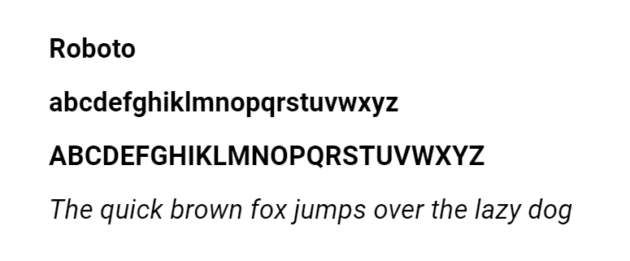
Les meilleures polices de sites Web et comment choisir la bonne
Publié: 2022-02-11De la palette de couleurs aux polices et à la conception du titre, chaque petit détail compte si nous parlons d'un grand projet numérique comme votre site Web. L'utilisation de différentes polices et effets de police peut avoir un impact à la fois négatif et positif sur vos utilisateurs, et c'est à vous de décider si cela sera positif ou négatif. L'équilibre, une manière harmonieuse de relier tous ces détails en une seule création bien organisée, est d'une importance primordiale pour chaque designer numérique.
Les polices et les effets de police sont le meilleur moyen d'atteindre cet équilibre car, pour la plupart des pages Web, la quantité la plus importante de données visuelles est occupée par le corps du texte, les titres et les en-têtes. Par conséquent, vous pouvez ajuster le nombre de détails simples et complexes afin d'obtenir le résultat parfait.
Ouvrir Sans
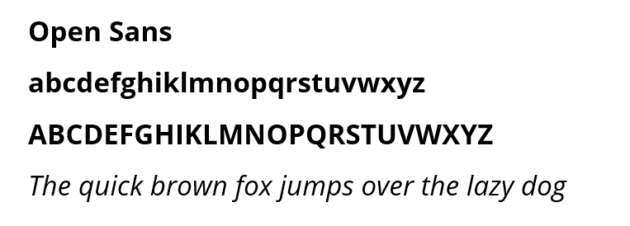
Open Sans fait partie des polices de caractères sans empattement destinées à offrir la meilleure lisibilité et expérience utilisateur. Cette police Web est le meilleur choix pour les sites Web minimalistes avec beaucoup d'informations à consommer (blogs, articles informatifs, etc.). Un autre grand avantage de cette police est sa compatibilité avec de nombreux styles différents.
Lato
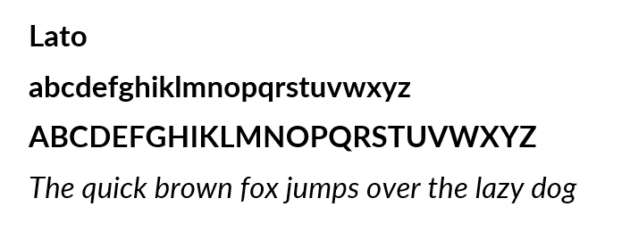
Lato est l'une des meilleures polices à utiliser si votre site Web s'active dans un domaine sévère tel que la finance, le droit ou même la comptabilité. Facile à utiliser, cette police de caractères de site Web est davantage considérée comme une police d'entreprise qui fait preuve d'un grand professionnalisme. Lato est la meilleure police pour ceux qui recherchent une manière moderne d'enrichir le design de leur site.
Helvétique
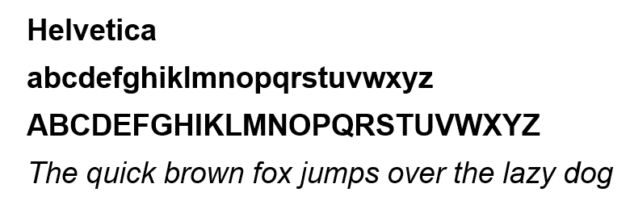
Étant l'une des polices de caractères les plus utilisées dans le monde, Helvetica a été mise au jour par Max Miedinger, un designer suisse. Helvetica a gagné sa popularité en raison de son incroyable variété de styles et de tailles, ce qui aide les concepteurs à choisir les meilleures versions pour leurs créations particulières.
Merriweather
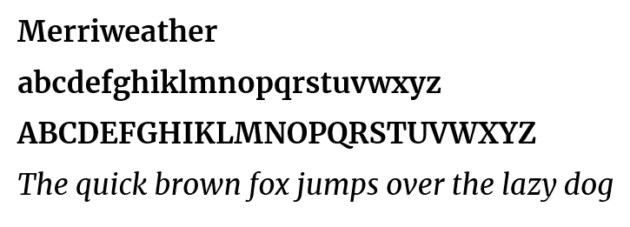
Si vous avez divers publics qui lisent votre contenu sur de grands et de petits écrans, la police du site Web Merriweather est celle que vous devez choisir. Cette police proportionnelle combine un look élégant avec une goutte de simplicité, une fusion phénoménale avec beaucoup de potentiel pour des sites dans divers domaines. Merriweather est parfait pour les styles formels et informels.
Présentoir Playfair
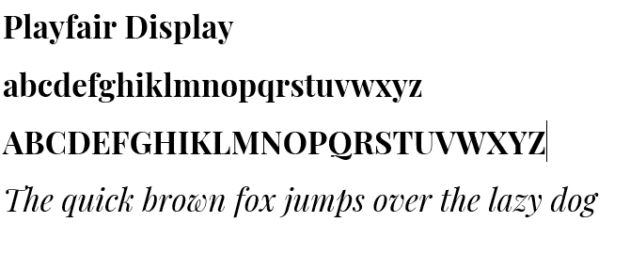
Playfair Display est une police élégante avec un peu de trait classique. Si vous choisissez une police pour un site Web sophistiqué, Playfair Display est définitivement votre choix. Il est parfait pour les sites Web légers et esthétiques avec un contenu facile à comprendre. En effet, Playfair Display n'est pas aussi lisible que les autres polices ; son principal avantage est la classe.
Montserrat
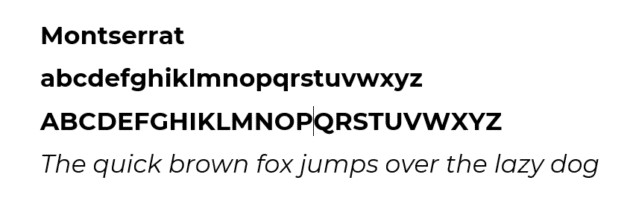
Cette police sans empattement est presque la meilleure police de site Web parmi laquelle vous pouvez choisir. Son style géométrique vous permet généralement de trouver un moyen de l'implémenter sur votre site Web. Bien que Montserrat soit très élégant, beaucoup de gens le trouvent lisible sur les petits et grands écrans.
Libre Baskerville
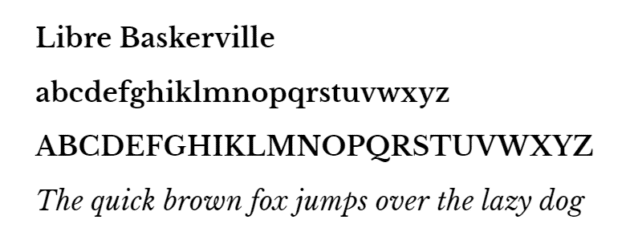
Libre Baskerville est une police à empattement inspirée de son prédécesseur du XVIIIe siècle. Son style classique est parfait pour une utilisation dans une grande variété de domaines tels que l'économie, le sport et la beauté. Bien que Libre Baskerville soit très populaire, ce n'est pas la meilleure option si votre public utilise de grands écrans pour accéder à votre site Web, car la police n'est pas très belle lorsque sa taille est trop grande.
Caudex
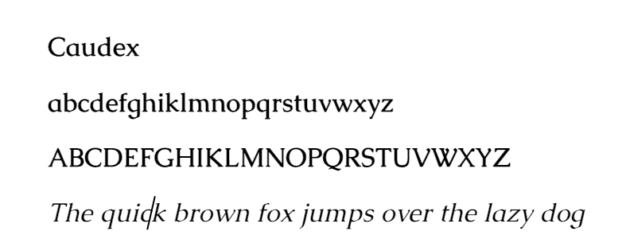
Initialement utilisé dans les manuscrits médiévaux, Caudex a été réformé et adapté à notre réalité à la fin des années 90 et n'a cessé de se développer depuis. Le Caudex peut être utilisé à la fois pour les paragraphes et les titres et est, sans aucun doute, la police avec la plus grande variété de styles disponibles. Il est idéal pour une utilisation sur grand et petit écran.
Barlow
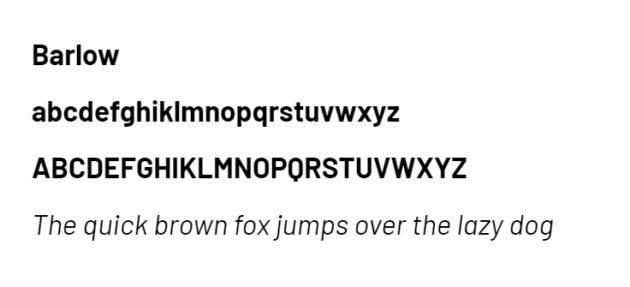
Cette police sans empattement Barlow semble s'inspirer des plaques d'immatriculation et des panneaux routiers californiens. Son design épuré peut apporter une certaine douceur à votre site Web, le rendant plus confortable et facile à lire. Un autre grand avantage de cette police de caractères est la compatibilité avec de nombreuses autres polices que l'on peut trouver sur votre site Web.
- Ne compliquez pas trop le design avec beaucoup de beaux mais inutiles qui ne feront qu'empirer les choses. Par exemple, c'est une bonne chose d'utiliser une police bien conçue pour les titres et les en-têtes. Mais pour le corps du texte, il est plus raisonnable de choisir une police de base comme Robotica ou Helvetica.